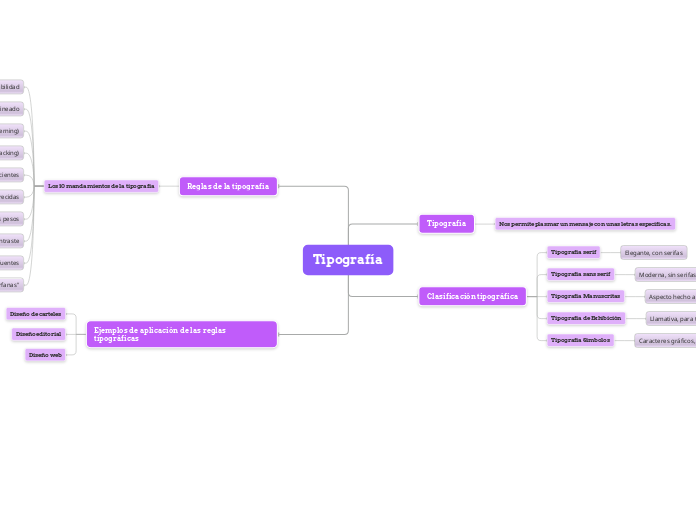
Tipografía, ¿Qué es?, Clasificación tipográfica, reglas(los 10 mandamientos de la tipografía)
La tipografía es una herramienta esencial en el diseño gráfico y editorial, permitiendo transmitir mensajes con claridad y estilo. Existen diversas categorías, como las tipografías serif, conocidas por su elegancia y serifas, y las sans serif, que destacan por su modernidad y ausencia de serifas.
Tipografía, ¿Qué es?, Clasificación tipográfica, reglas(los 10 mandamientos de la tipografía)
Tipografía
Ejemplos de aplicación de las reglas tipográficas
Diseño web
Diseño editorial
Diseño de carteles
Reglas de la tipografía
Los 10 mandamientos de la tipografía
10.-Cuidado con las "viudas" y las "huérfanas"
9.-No distorsiones las fuentes
8.-Cuida el contraste
7.-Mezclar varios pesos
6.-No usar tipografías muy parecidas
5.-Dos tipografías son suficientes
4.-Espaciado (tracking)
3.-Interletraje (kerning)
2.-Interlineado
1.-Prioriza la legibilidad
Clasificación tipográfica
Tipografía Símbolos
Caracteres gráficos, iconos.
Tipografía de Exhibición
Llamativa, para títulos.
Tipografía Manuscritas
Aspecto hecho a mano.
Tipografía sans serif
Moderna, sin serifas
Tipografía serif
Elegante, con serifas
Nos permite plasmar un mensaje con unas letras específicas.